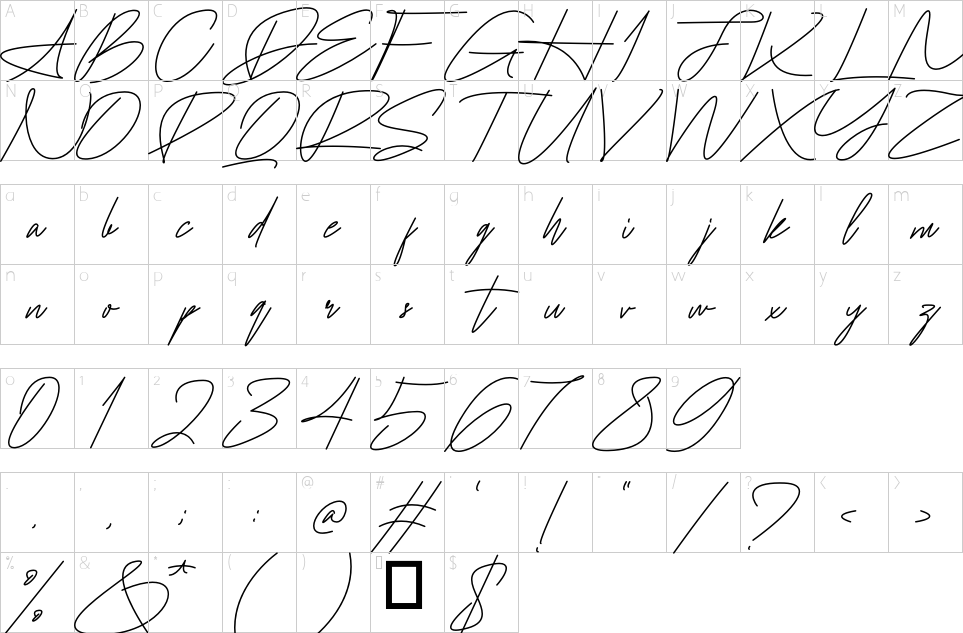
Jouminton é uma fonte grata que se destaca por sua elegância e facilidade de uso. Desenvolvida pelo designer Jada Akbal, ela é uma escolha ideal para projetos que buscam um equilíbrio perfeito entre modernidade e estética clássica. Suas linhas leves e atraentes garantem um texto legível e agradável para qualquer projeto, seja ele um site personalizado ou um documento profissional. Com uma baixa demanda, Jouminton oferece uma opção exclusiva de fonte, que muitos designers podem valorizar pela sua qualidade e simplicidade. Download a Jouminton para Windows e Mac hoje e experimente esta fonte moderna e elegante, perfeita para qualquer projeto.